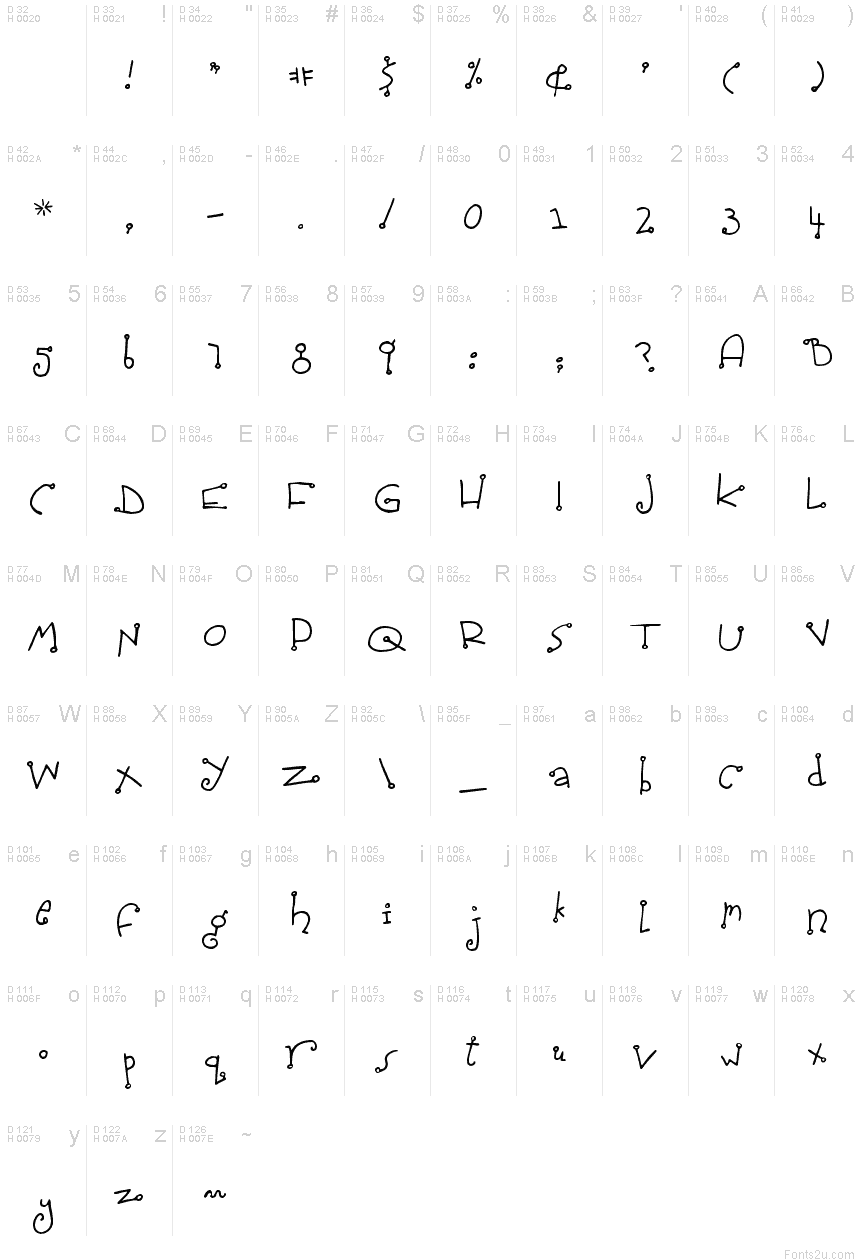
Spidershank od Uddi Uddi to darmowy krój pisma typu cartoon z wydłużonymi, odręcznie rysowanymi literami, które są jednocześnie lekko mroczne i zabawne. Kreski układają się jak luźny drut i kończą zaokrąglonymi kropkami i pętelkami, co nadaje całości pajęczy, nabazgrany rytm, daleki od wygładzonej komiksowej estetyki.
Pasuje do plakatów na Halloween, okładek niezależnych zinów, dziecięcych projektów naukowych, kreatywnych opakowań i dziwacznych nagłówków, gdzie litery zachowują się jak postacie na stronie. Jako darmowy font sprawdza się również w krótkich nagłówkach, ulotkach wydarzeń czy tematycznych postach w mediach społecznościowych, zwłaszcza gdy chcesz, aby ta wisząca, przypominająca owada sylwetka od razu przyciągnęła wzrok.